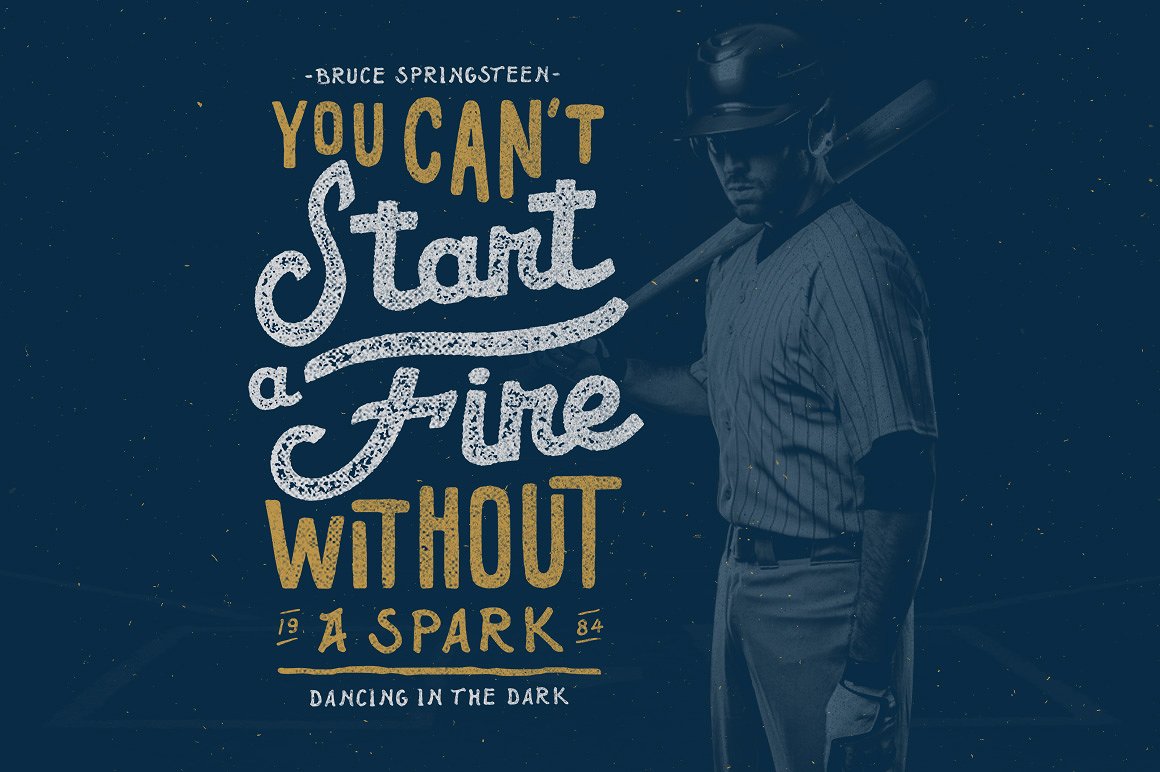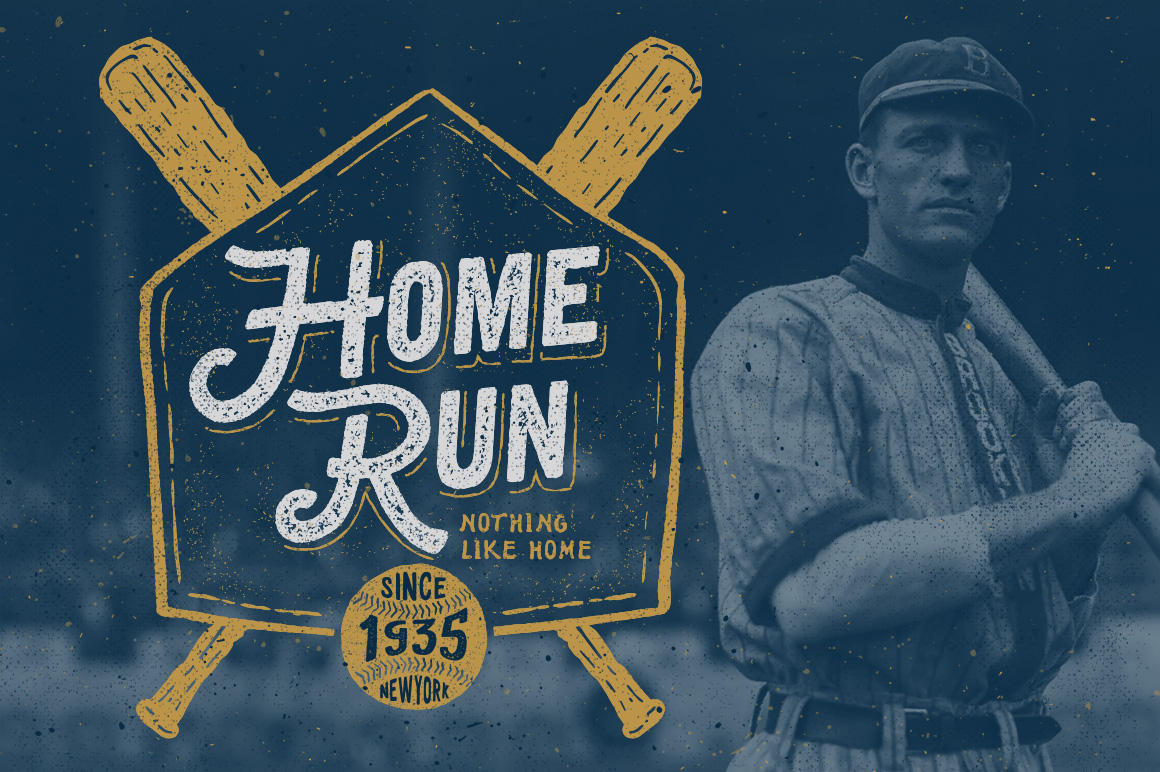
Font American Forkball việt hóa - Kiểu font bút lông
Font American Forkball việt hóa - Font này phù hợp để sử dụng quote design, thiết kế áo phông, bao bì, menu đồ ăn uống v..v. Font VH bởi iCiel.
Bộ font bao gồm:
- 2 font American Forkball việt hóa chính gồm 2 style smooth và textured
- 1 font Captain's Talk việt hóa
- 1 font White woods việt hóa